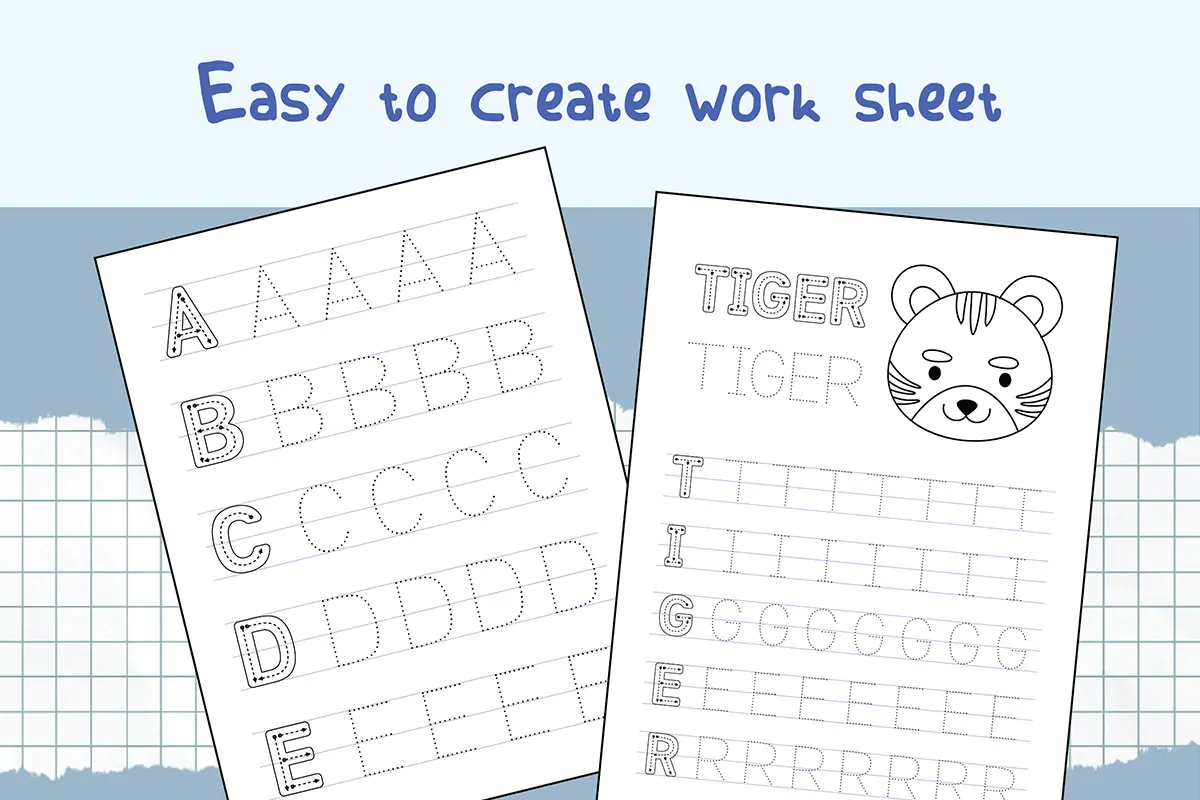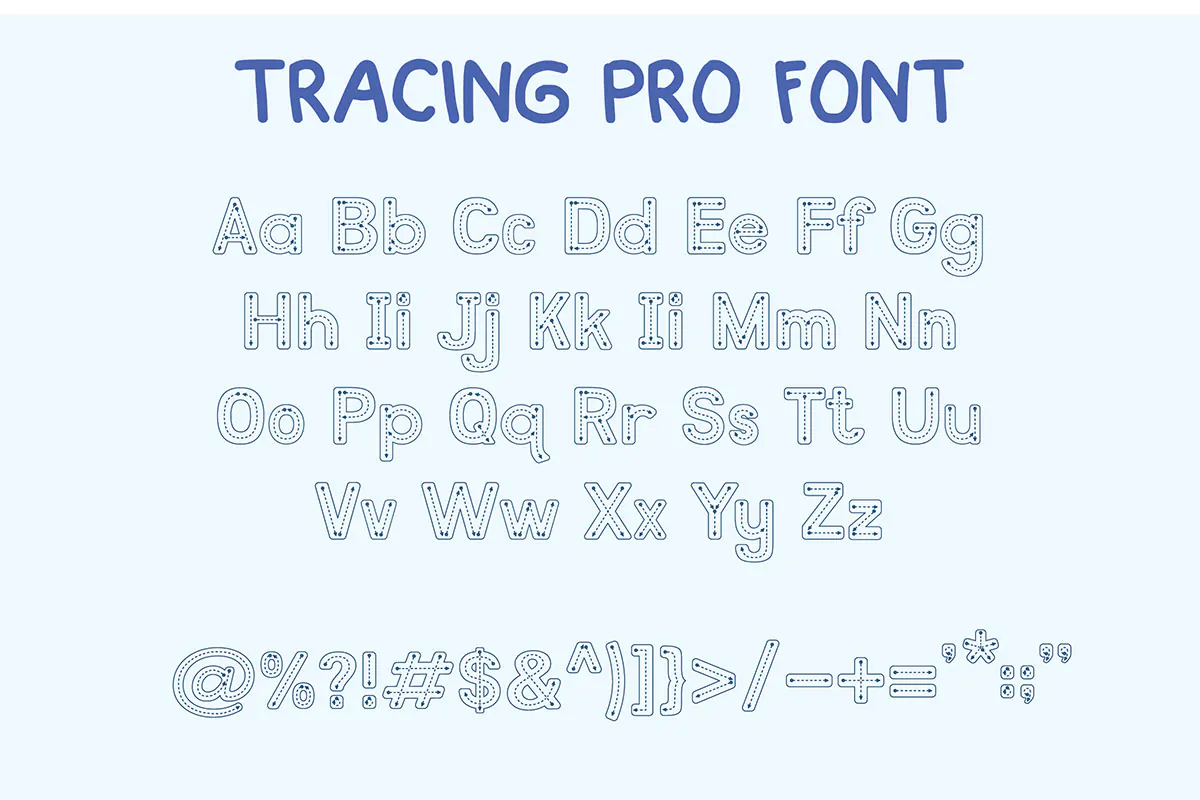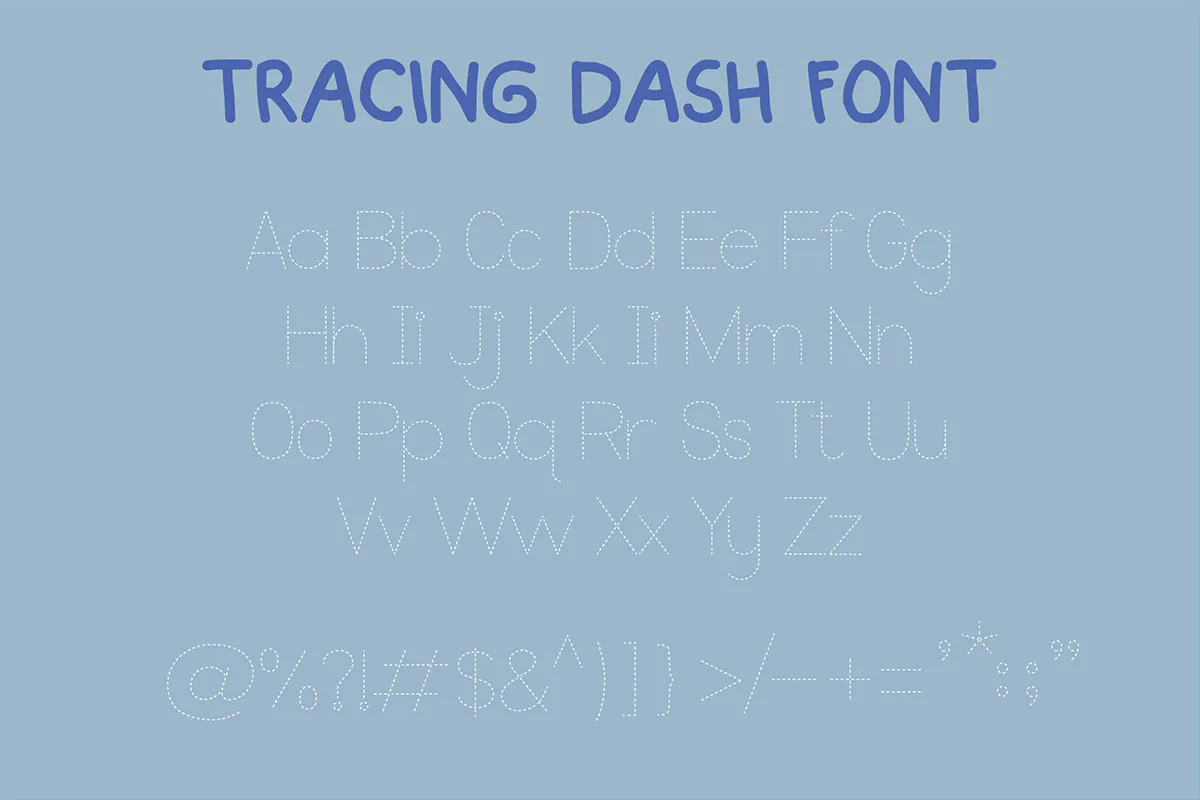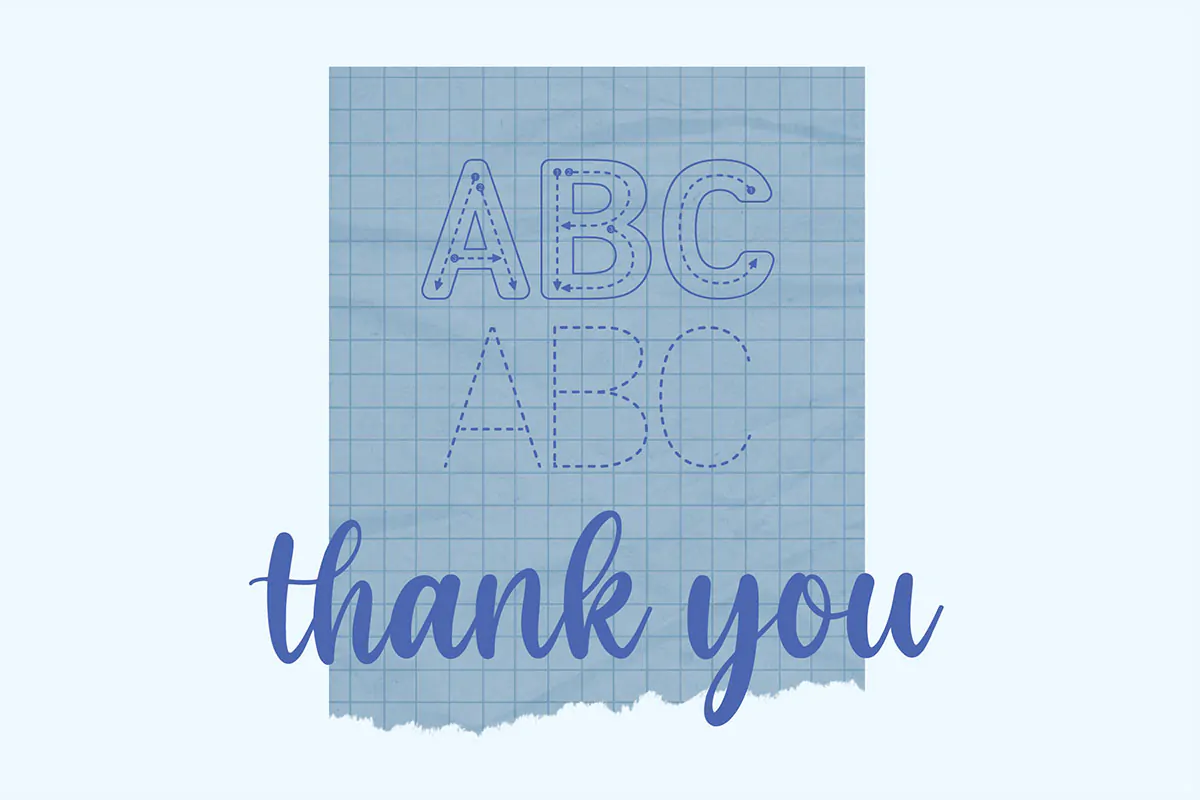
فونت آموزش نوشتن حروف الفبای انگلیسی
فونت خط چین Tracing Pro
فونت خط چین Tracing Pro یک قلم انگلیسی مناسب برای آموزش نوشتن حروف الفبای انگلیسی است که میتوان از آن در طراحی کتب آموزشی، انواع لوح، طرح و پروژههای گرافیکی و … استفاده نمود.